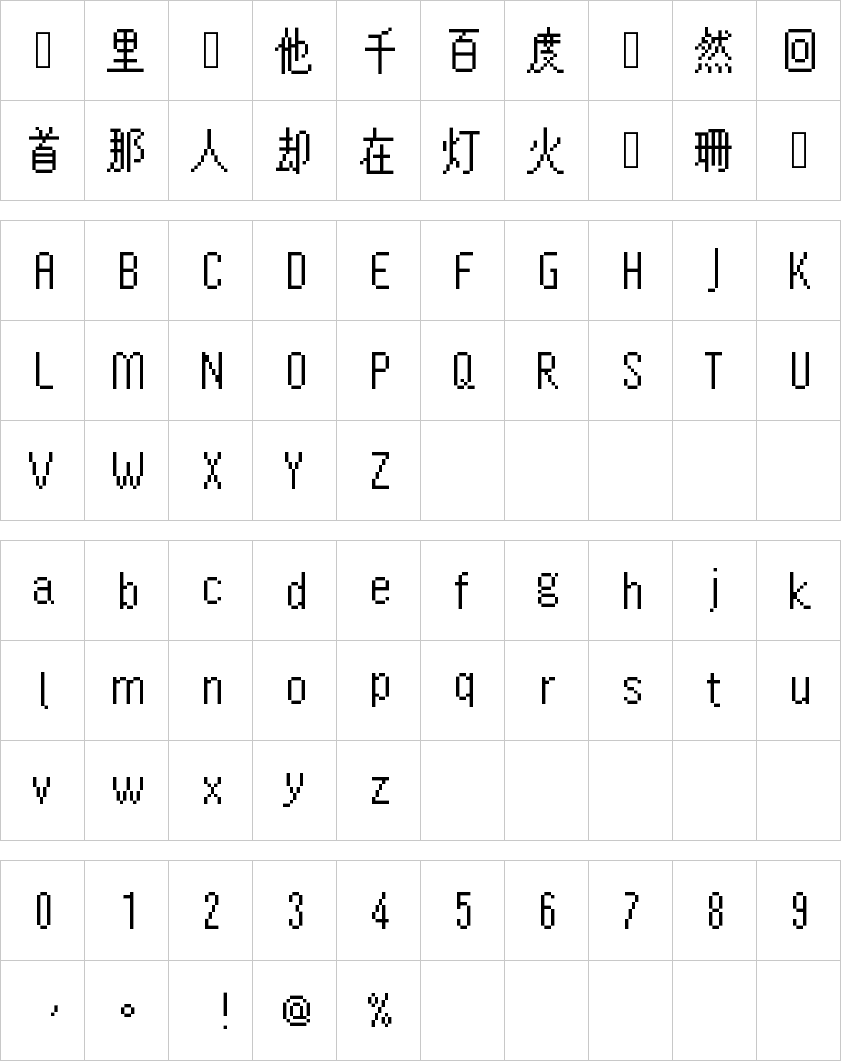
x12y16pxMaruMonica
■追求像素形成的曲线美。
是兼具“柔软”和“严肃”的像素字体。
JIS第1水准汉字2965字,第2水准汉字3390字完全收录!
打印标准字体1022字也对应。
■美丽的欧文,充实的多语言对应。
支持使用拉丁文字、西里尔文字的多种语言。
通过独特的字间调节,即使在没有字距调整功能的游戏开发环境中也能实现自然美丽的欧文表示。